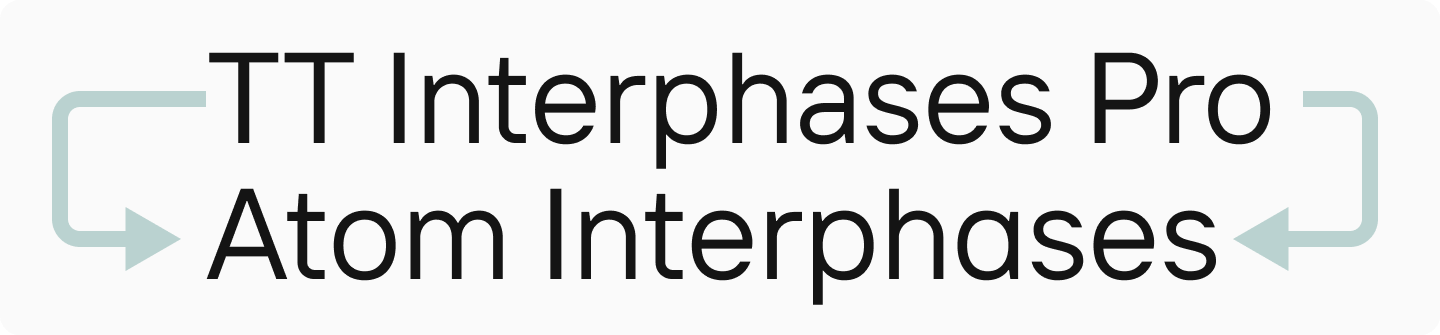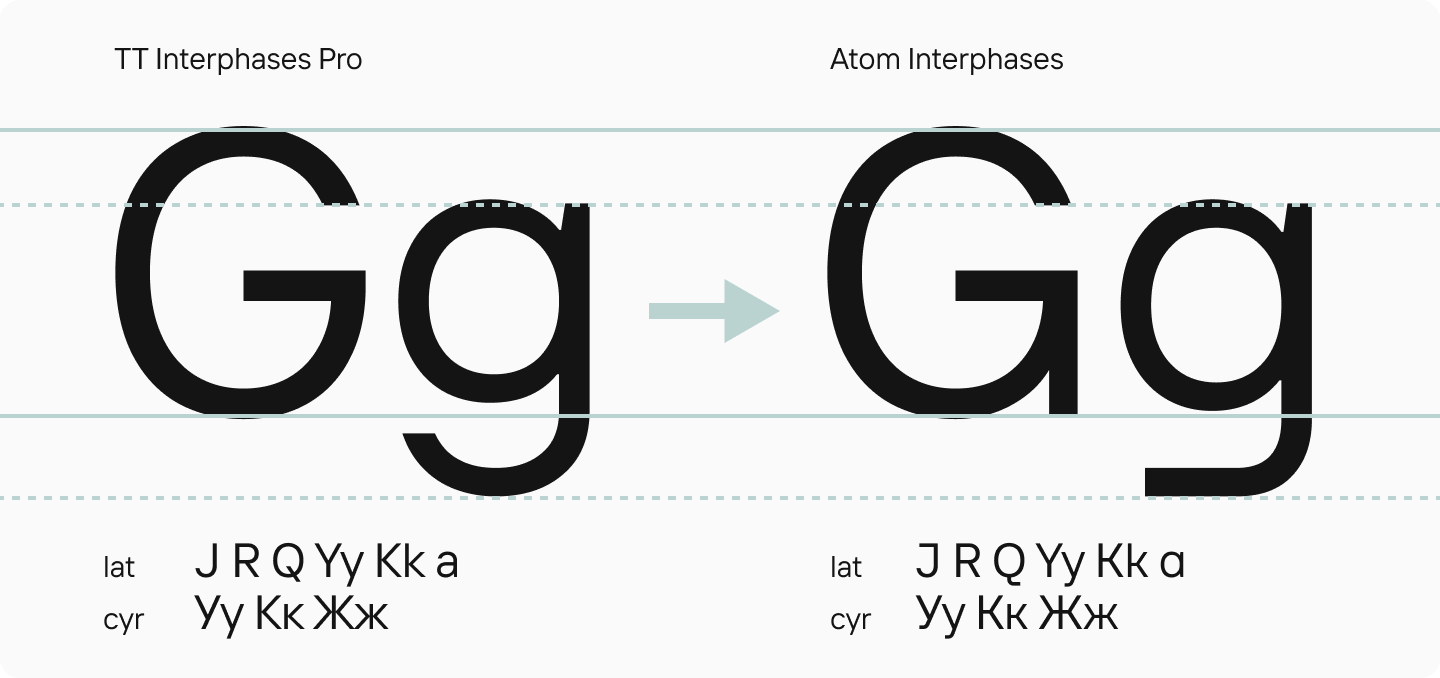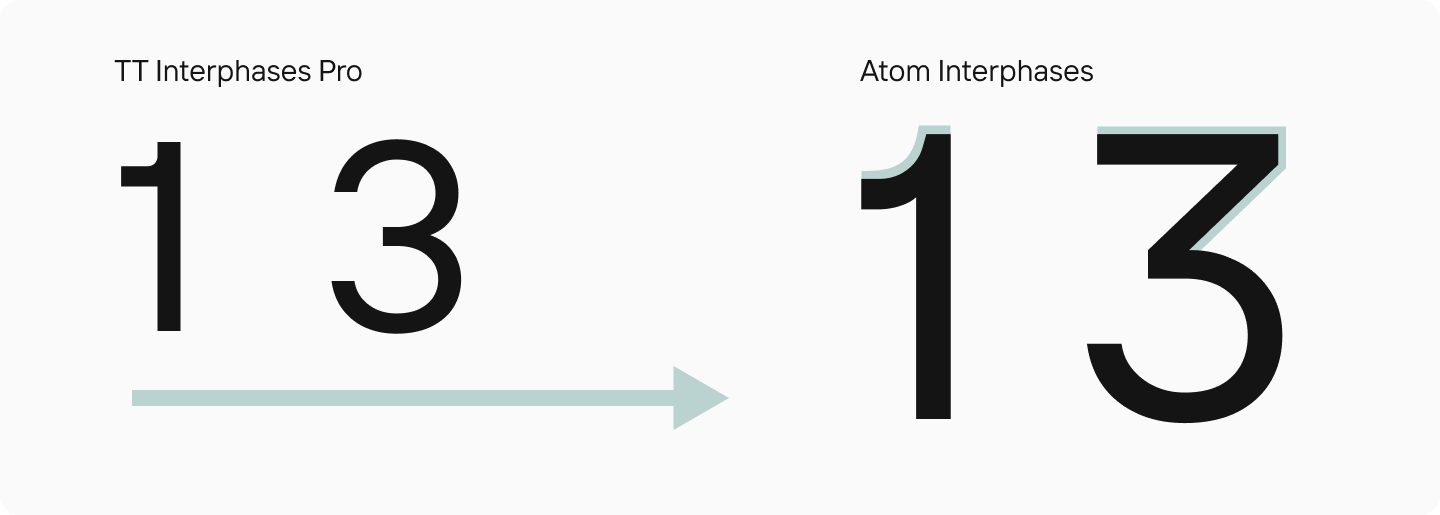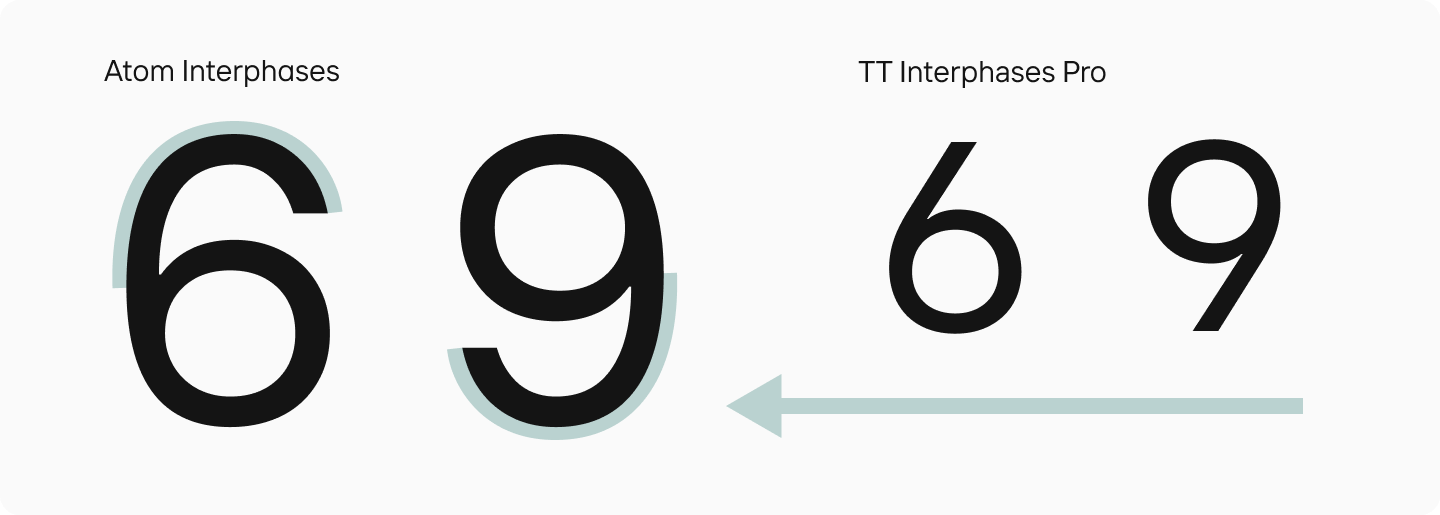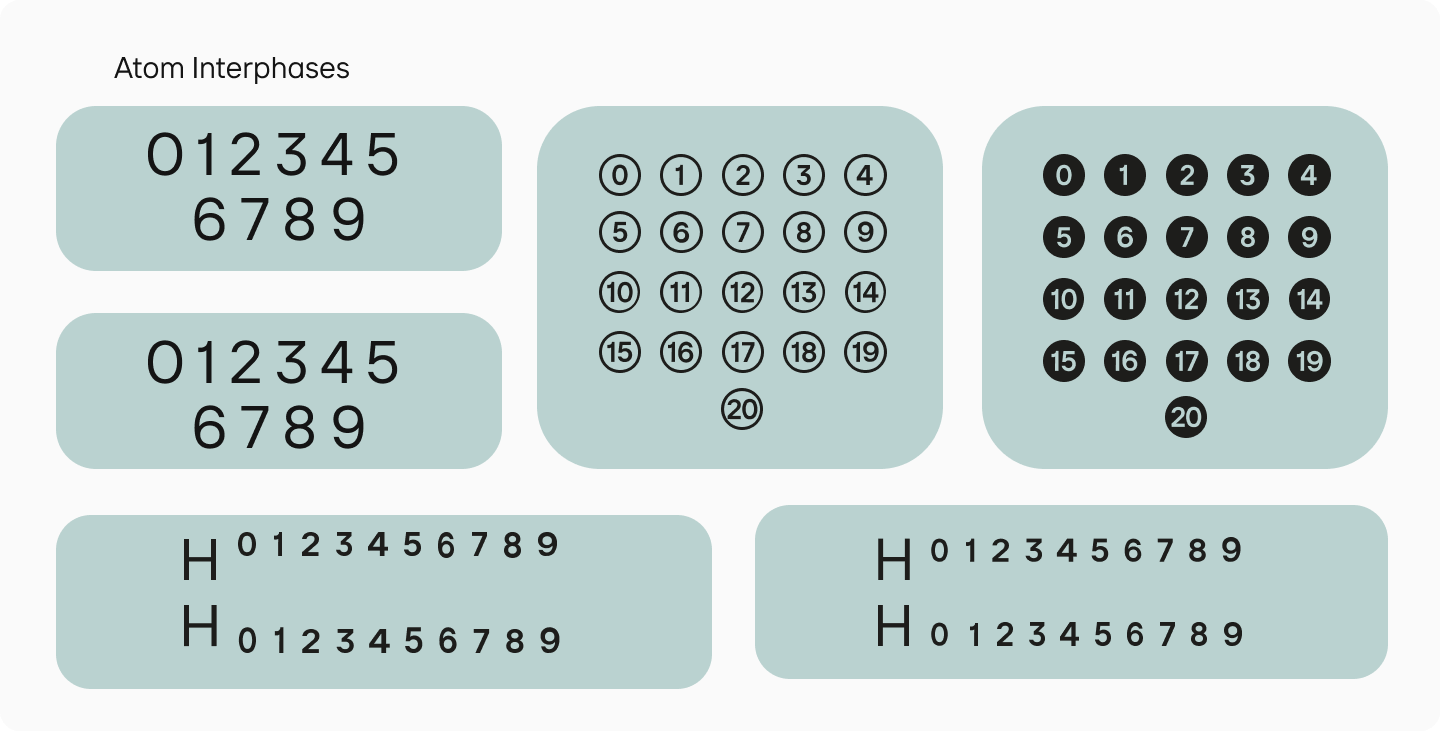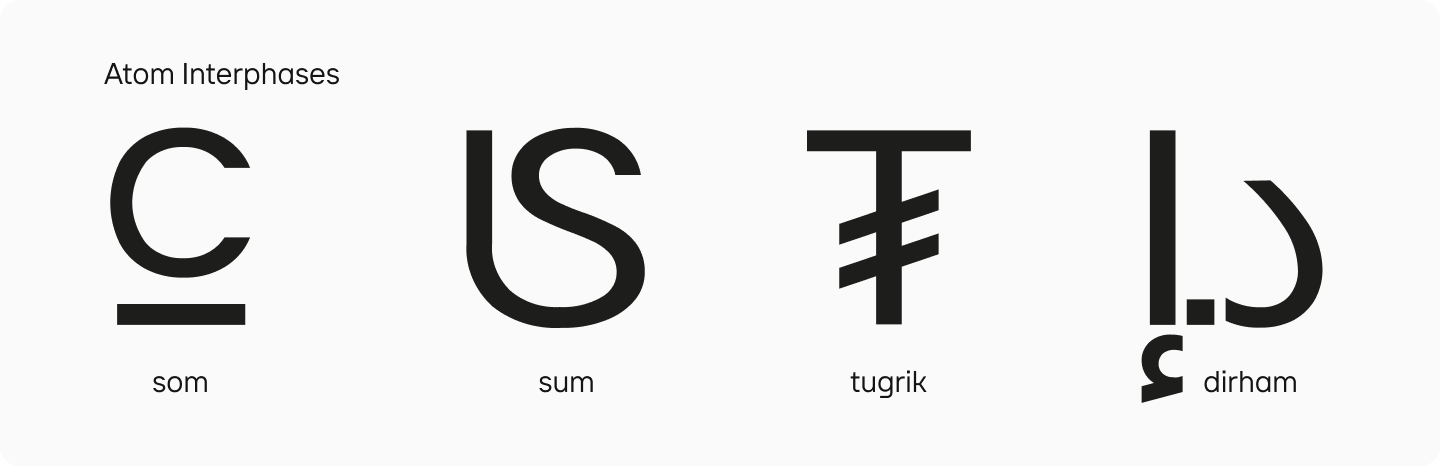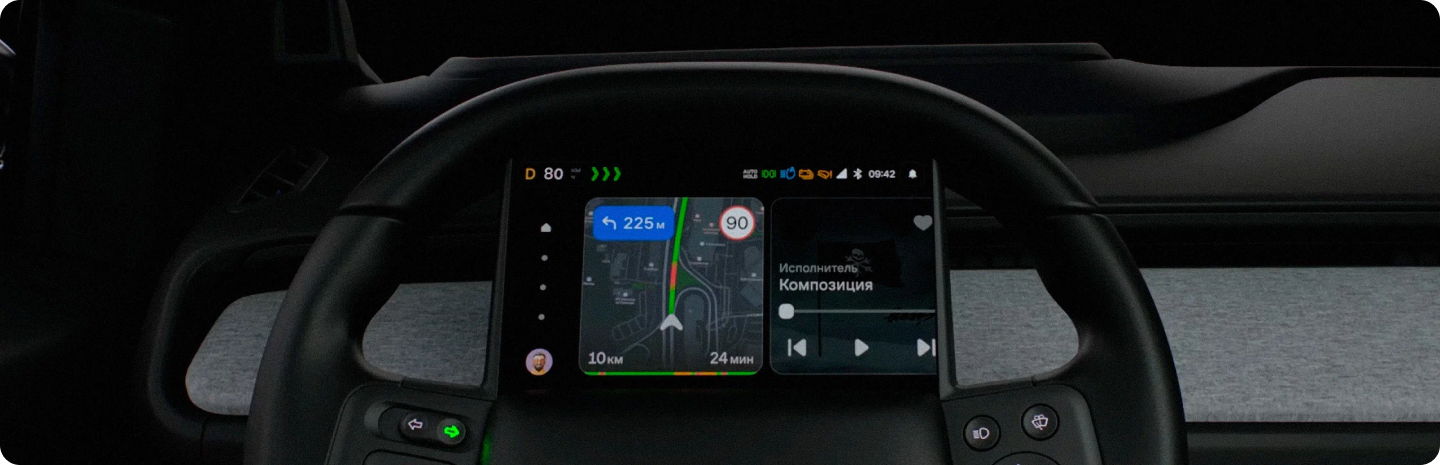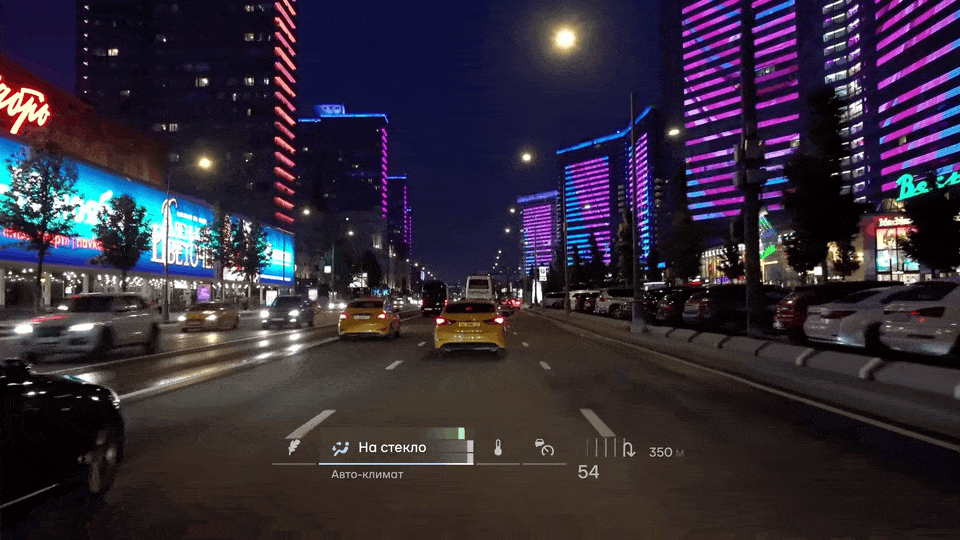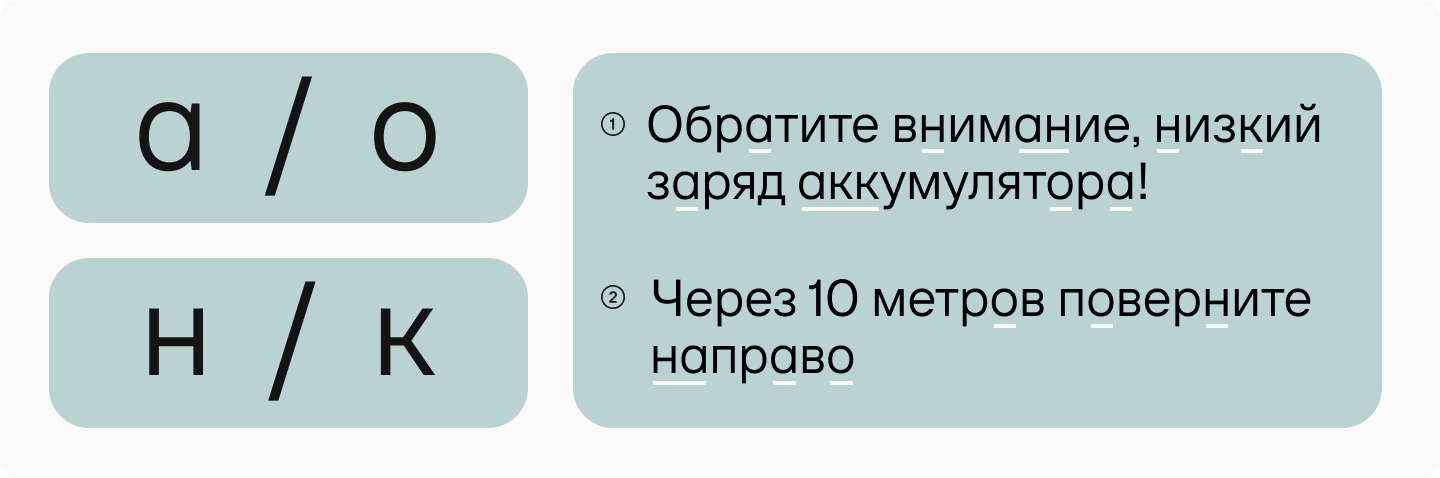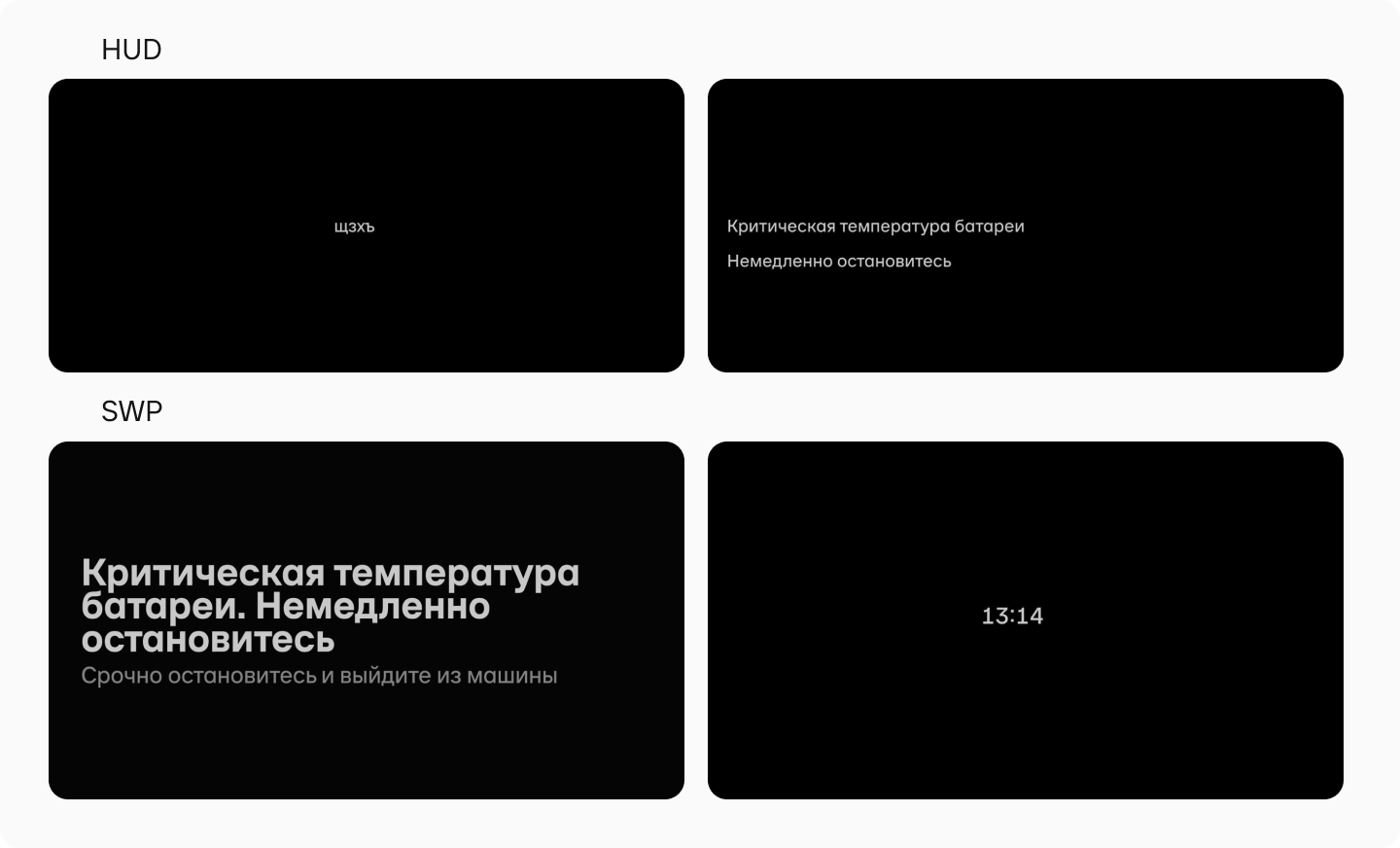
Atom Interphases: кастомизация шрифта для Атома
Атом — первый российский серийный электромобиль, выпуск которого ожидается совсем скоро. Уже сейчас завершаются испытания функциональных прототипов. Уникальный интерфейс этого гаджета — настоящий привет из будущего: здесь и дополненная реальность, и дисплей-проекция на лобовом стекле (AR HUD), и экран прямо в руле (SWP). Подробнее о том, как устроен электромобиль, читайте здесь.
Перед TypeType стояла задача создать текстовый шрифт для интерфейса электромобиля, приложения, сайта и всех остальных площадок Атома. При этом он должен был сочетаться с дисплейным шрифтом Atom, который уже использовался в проекте. На этапе согласования мы с командой Атома пришли к выводу, что лучшим решением будет кастомизация нашего шрифта TT Interphases Pro.
«Наша мечта — создать единство стиля коммуникации с пользователем на всех медианосителях. От постеров до интерфейсов в электромобиле. Шрифт Atom — яркий неогротеск, он помогает нам выделяться в информационном шуме. Но UI-команда предпочитает более строгие шрифты с минимальной когнитивной нагрузкой на водителя. По их запросу мы провели подбор шрифтовых пар, и всем понравился TT Interphases Pro. Нам хотелось добавить ему характер бренда Атом. И здесь TypeType предложили нам отличное решение по кастомизации своего шрифта».
Олег Вахромеев, креативный директор Атома
«Нам нужно было добавить брендинговую составляющую в шрифт. Поэтому мы решили сделать некоторые знаки более интересными, акцидентными. При этом очень важно было сохранить читабельность».
Антонина Жулькова, дизайн-лид TypeType
Чтобы характер кастомизированного шрифта перекликался с существующим дисплейным, мы выбрали характерные буквы и, опираясь на них, изменили ряд знаков в TT Interphases Pro. В частности, «G», «J», «R», «Q», «a» и «g», у которых менялись терминалы, а также «Уу», «Yy», «Кк» «Kk» и «Жж». Некоторые формы мы перерисовали заново.
Цифры также подверглись изменениям в сторону большей яркости и характерности. В частности, цифры 1, 3, 6 и 9 во всех регистрах — большие, маленькие, табулярные, все цифры в кружочках и так далее.
«Интересная история получилась с цифрами 6 и 9. В оригинальном TT Interphases Pro они выглядели как кружок с диагональной линией. Чтобы сделать эти формы более дисплейными, нужно было добавить им «хвосты». Но для читабельности такая форма не очень хороша, потому что она не такая однозначная: можно перепутать эти цифры с восьмёркой, с тройкой, с нулём. Поэтому мы сделали два набора для разных задач: одни более читабельные, другие более акцидентные».
Антонина Жулькова, дизайн-лид TypeType
Для интерфейсов мы сделали отдельный шрифт, в который вошли только табулярные цифры — они используются именно в тех случаях, когда необходима различимость цифр при большой скорости считывания.
Также мы дорисовали валюты сом, сум, тугрик и дирхам во всех регистрах. Особенно интересно было работать с дирхамом, потому что мы никогда ранее не делали этот символ. В настоящее время дирхам является национальной валютой Объединённых Арабских Эмиратов и Марокко, а также разменной денежной единицей Иордании, Ливии и Катара. Она не имеет отдельного символа для обозначения, как, например, знак рубля или доллара, и набирается с помощью трёх отдельных символов: двух знаков арабской вязи и точки.
Однако для этого шрифта мы сделали отдельный глиф для дирхама, чтобы было удобно его набирать. И даже провели небольшое исследование, чтобы понять, как именно он должен выглядеть в таком шрифте.
Также мы доработали шрифт технически: настроили базовую линию интерлиньяжа, чтобы при внедрении в интерфейс при замене одного шрифта на другой сохранилась вёрстка.
Получившийся шрифт получил название Atom Interphases. Он полностью решил задачи компании, и исследование Атома, о которым мы расскажем далее, это подтверждает.
Исследование шрифта для интерфейсов Атома
После того, как мы передали готовый Atom Interphases, команда Атома решила протестировать шрифт, воссоздав условия поездки. Было важно понять, насколько быстро и просто считываются уведомления, ведь это напрямую влияет на безопасность поездки.
«Мы проверяли, подходит ли шрифт под конкретные интерфейсы: SWP — это планшет на руле, и HUD — проекция на лобовое стекло. Необходимо было проверить читабельность и распознаваемость символов с учётом именно этих специфических интерфейсов, узнать, как шрифт поведет себя в условиях, когда человек едет на машине по дороге».
Ярослава Медведева, ведущий исследователь пользовательского опыта в бренде Атом
Подготовка
Сама структура исследования была довольно простой. Всё началось с брифинга с командами Атома и TypeType. Специалисты обсудили потенциальные проблемы, которые могут возникнуть в заданных условиях: как считываются конкретные буквы, не будут ли они путаться. Например, не будет ли одночастная «а» читаться как «о». Если будет, то несёт ли это какой-либо риск. Как буквы и символы распознаются в целом.